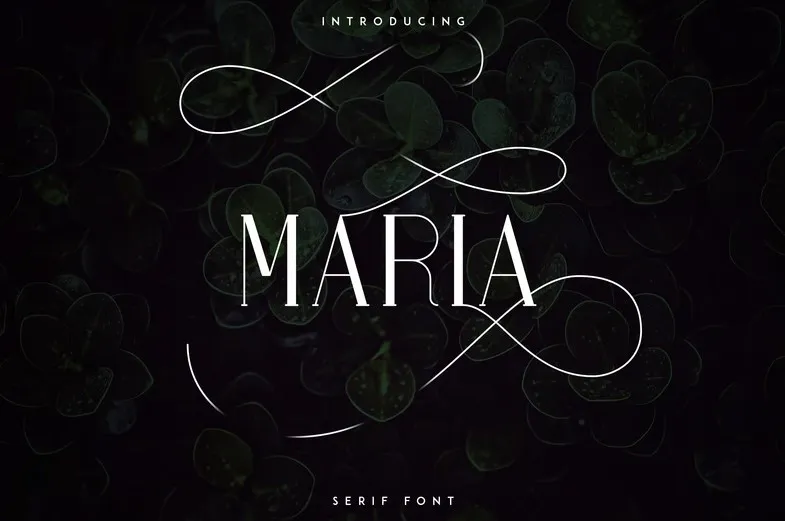
Maria Serif Font – Download Grátis
A Maria Serif Font é uma elegante tipografia serifada com suporte a múltiplos idiomas, oferecendo 10 alternativas de letras para cada letra, criando um design que te encantará. Perfeita tanto para ambientes grandes quanto menores, ela permite diferentes efeitos no seu projeto. Esta fonte é versátil o suficiente para ser usada em qualquer tipo de projeto gráfico: desde atraentes banners até belos textos legíveis em um site ou revista. A Maria Serif Font não só adicionará sofisticação e elegância a seus projetos, mas também fará sua marca mais profissional e memorável. Ideal tanto para designers profissionais quanto para iniciantes que procuram dar vida às suas criações de design.